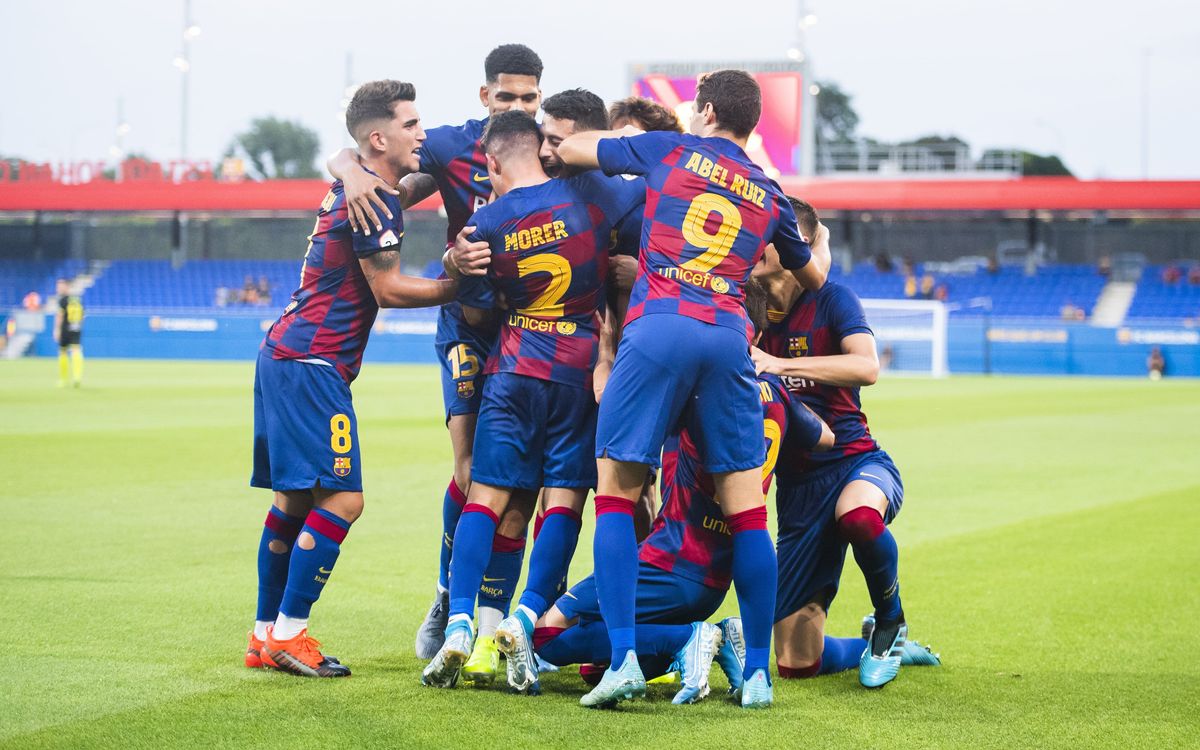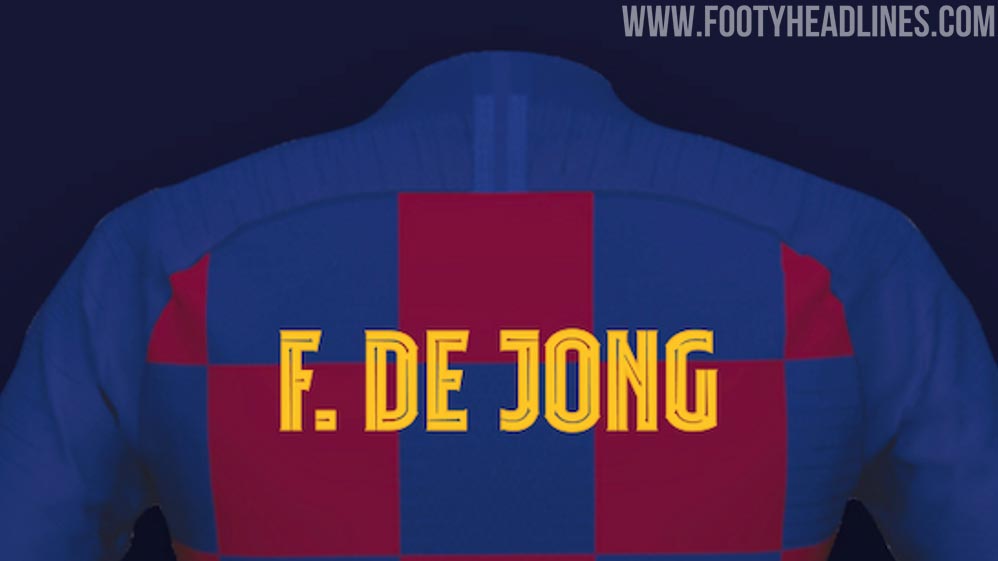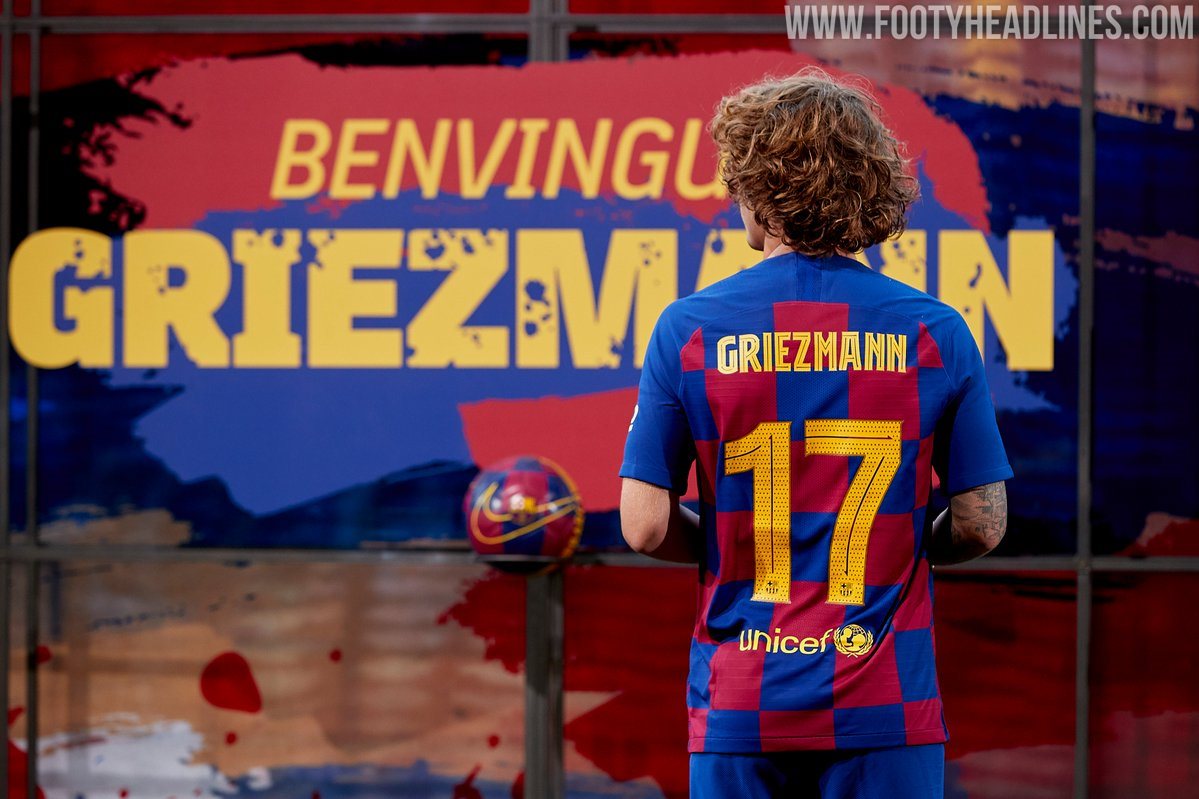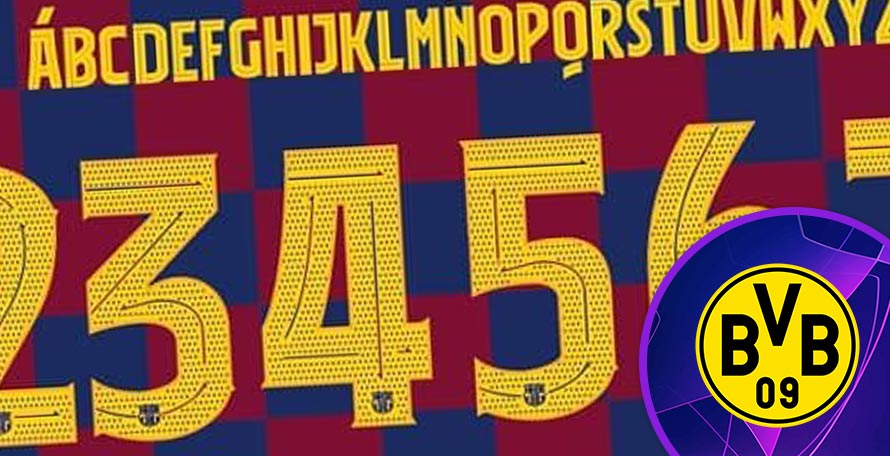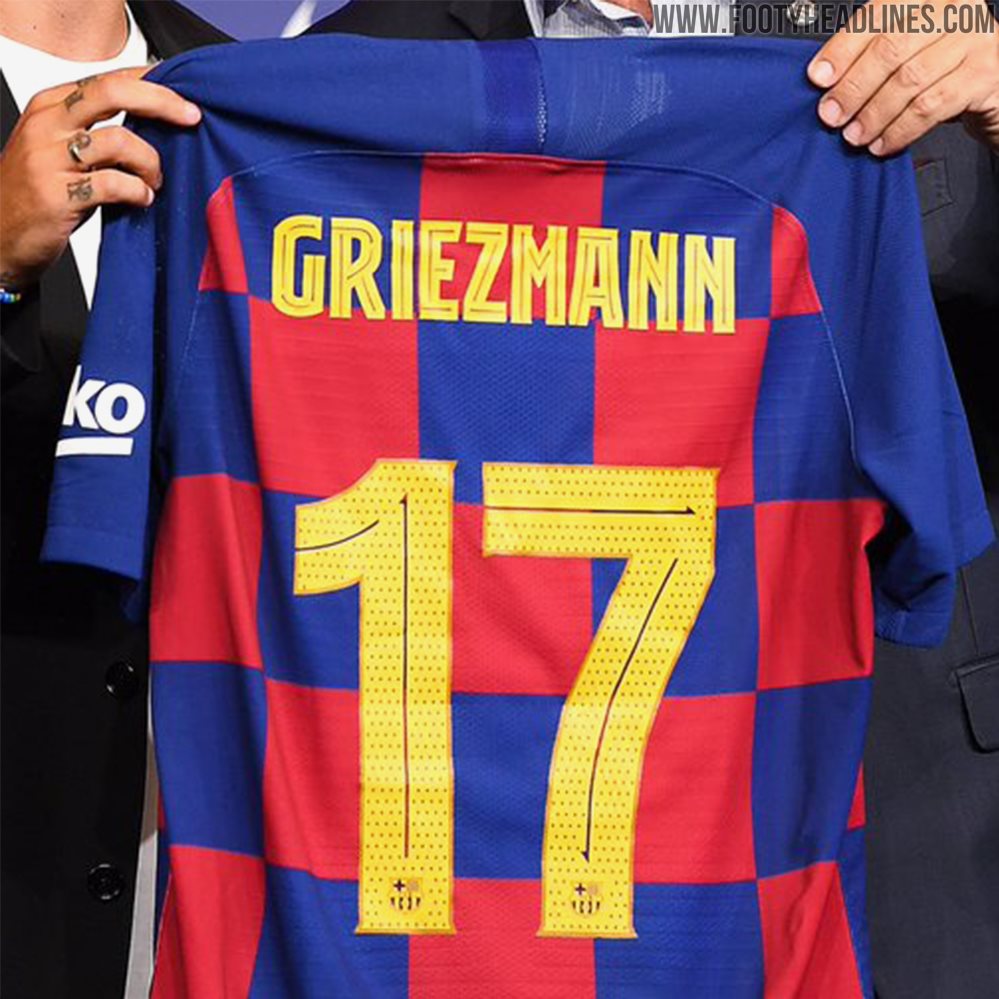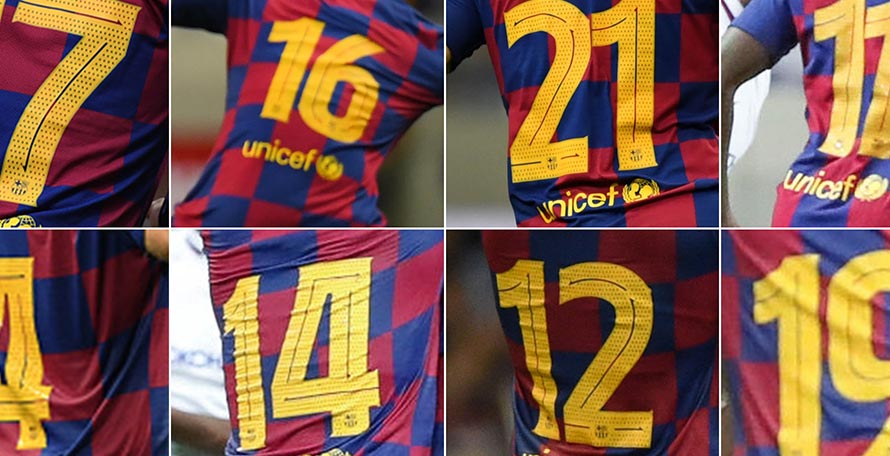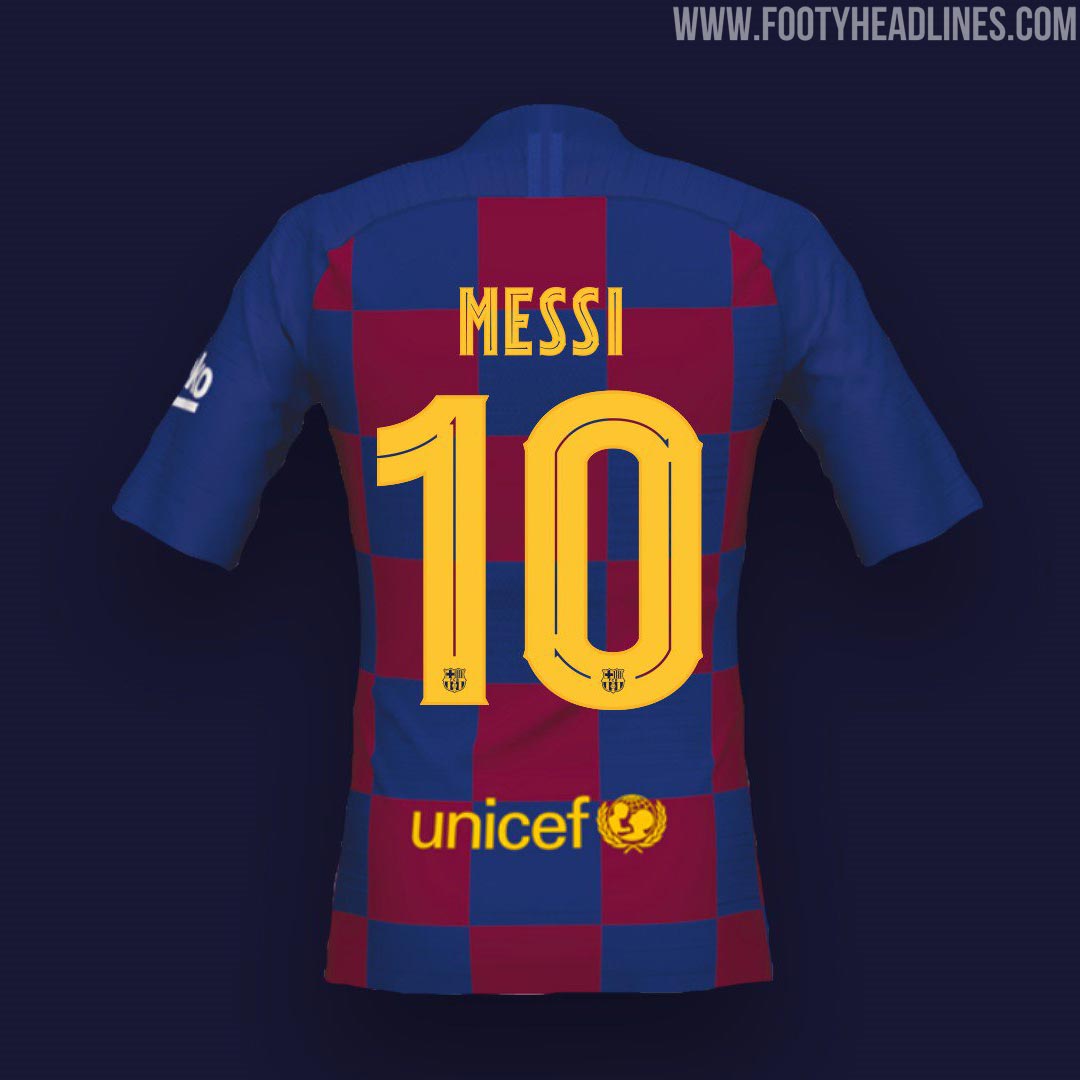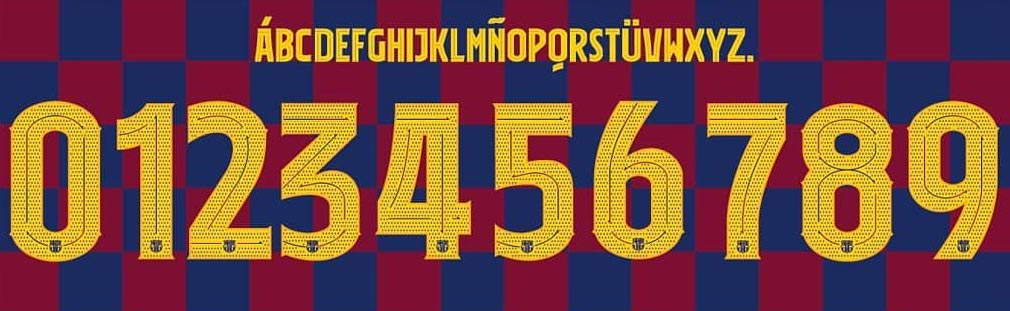
Offizielles Debüt vor der Tür: Komplette FC Barcelona 19-20 Schriftart Enthüllt - Champions League Exklusiv
Update: Barcelonas erste Mannschaft wird die neue Schriftart endlich im ersten Champions League Spiel auswärts gegen Dortmund nächsten Dienstag debütieren.
Die "B" und Jugendteams des Klubs haben die Schriftart bereits in ihren ersten Ligaspielen der neuen Saison verwendet und jetzt sollen Leo Messi und Co. folgen. Leider ist die Schriftart nach wie vor nur für jene verfügbar, die an einem physischen Standort wie dem berühmten Camp Nou Store einkaufen.
Update: Nach den ersten beiden Spielen der Saisonvorbereitung haben wir einen Blick auf Bilder aus dem Spiel geworfen, um Dir einen besseren Blick auf die neue Klub-Schriftart zu liefern, "FC Barcelona Play". Leider ist die Schriftart nirgends online erhältlich und kann nur in den örtlichen offiziellen Klub-Shops erworben werden.
Einen Tag nach der Präsentation von Frenkie de Jong hat der FC Barcelona heute offiziell seine brandneue Schriftart "FC Barcelona Play" vorgestellt.
Die Schriftart FC Barcelona Play wird von der Fußballmannschaft bei allen Wettbewerben verwendet, die die Verwendung eines individuellen Designs nicht verbieten: vor allem bei der UEFA Champions League, aber auch bei Freundschaftsspielen und dem Copa del Rey-Finale. In der Liga wird Barcelona, wie in den beiden Vorsaisons, weiterhin das Schriftdesign der La Liga verwenden.
Im Jahr 2017 führte La Liga eine einheitliche Schriftart ein, die von allen Mannschaften der spanischen ersten Liga verwendet werden soll, ähnlich wie die Premier League. Real Madrid war damit wirklich unzufrieden und hat sogar eine Klage eingereicht, weil man sich nicht zwingen lassen wollte, die La Ligas Schriftart zu benutzen. Real Madrid verwendete in der Champions League eine eigene Schriftart und nie die La-Liga-Schriftart, jedoch im Gegensatz zu Barcelona.
Die FC Barcelona Play 19-20 Schriftart, die von de Jong sowie anderen Neuverpflichtungen Barcelonas diese Saison wie dem neuen FCB Basket Spieler Cory Higgins präsentiert wird, führt ein völlig neues Design ein.
FC Barcelona 2019-2020 Trikot-Schriftart
So wird Messis Trikot in der nächsten Saison aussehen.
Die neue Nike FC Barcelona 19-20 Trikot-Schriftart zeichnet sich durch ein stilvolleres Design aus als die ligaweite La Liga Schriftart. Die Buchstaben haben ein kantiges Design mit einer dünnen Linie, die Nummern setzen auf das Barca-Wappen. Ein weiterer Unterschied besteht darin, dass die Spielernamen gerade ausgerichtet sind und nicht auf einer Kurve wie bei der Ligaschrift.
Obwohl Barcelona bereits früher exklusive Schriftartendesigns hatte, stellte sich der Club zum ersten Mal der Herausforderung, ein neues Design zu entwickeln, da frühere Schriftarten von Nike erschaffen wurden.
Konzeptionell ist FC Barcelona Play eine Typografie, die auf den Ursprüngen und der Geschichte des Klubs, der katalanischen Moderne im späten 19. Jahrhundert und insbesondere auf der direkten Verbindung zwischen Barça und den aktuellen künstlerischen und ästhetischen Trends in der Stadt Barcelona und Katalonien basiert. Die Absicht war, dass jedes Wort, das mit der Typographie geschrieben wurde, seine eigene Persönlichkeit und Fähigkeit hatte, Varianten zu haben.